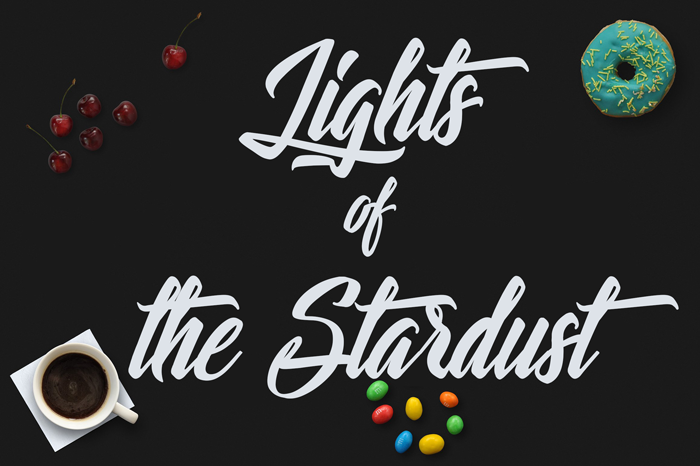
Lights of the Stardust Font – Download Grátis
A Octotype Lights of the Stardust Font é uma opção única para designers que desejam adicionar um toque especial a seus projetos digitais. Com um design fluido e moderno, esta fonte script oferece uma paleta de caracteres vibrante e versátil para textos gráficos, anúncios ou qualquer outro conteúdo onde você busque dar vida aos detalhes em seu trabalho. O que torna este projeto ainda mais interessante é a disponibilidade de uma licença comercial completa para quem desejar incorporar esta fonte em seus projetos. Octotype mantém um catálogo vasto e diversificado, e os usuários podem se beneficiar não apenas da sua beleza visual, mas também de um recurso que permite integrá-la de maneira contínua e econômica. Envolventemente elegante e prazerosa para usar em qualquer tipo de projeto, esta fonte é ideal para quem busca criar textos gráficos atraentes e autênticos. Seja na criação de sites, logotipos ou até mesmo design editorial, Lights of the Stardust se destaca por ser tanto funcional quanto bonito. Acessar e baixar esta fonte é uma ótima maneira de adicionar um detalhe único a seus projetos, oferecendo à sua marca uma identidade visual moderna e impactante.